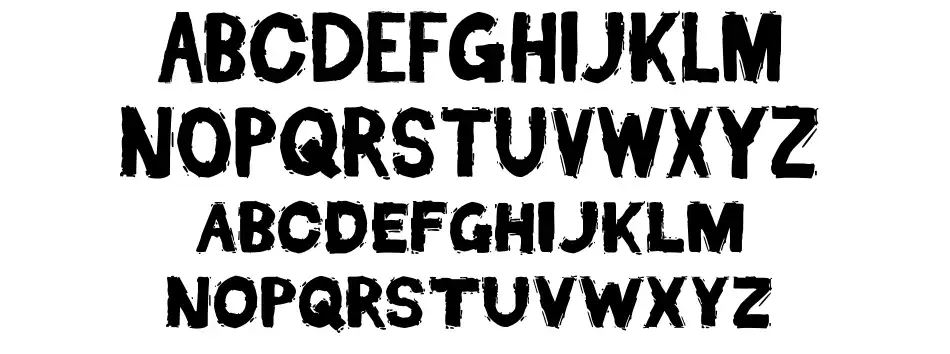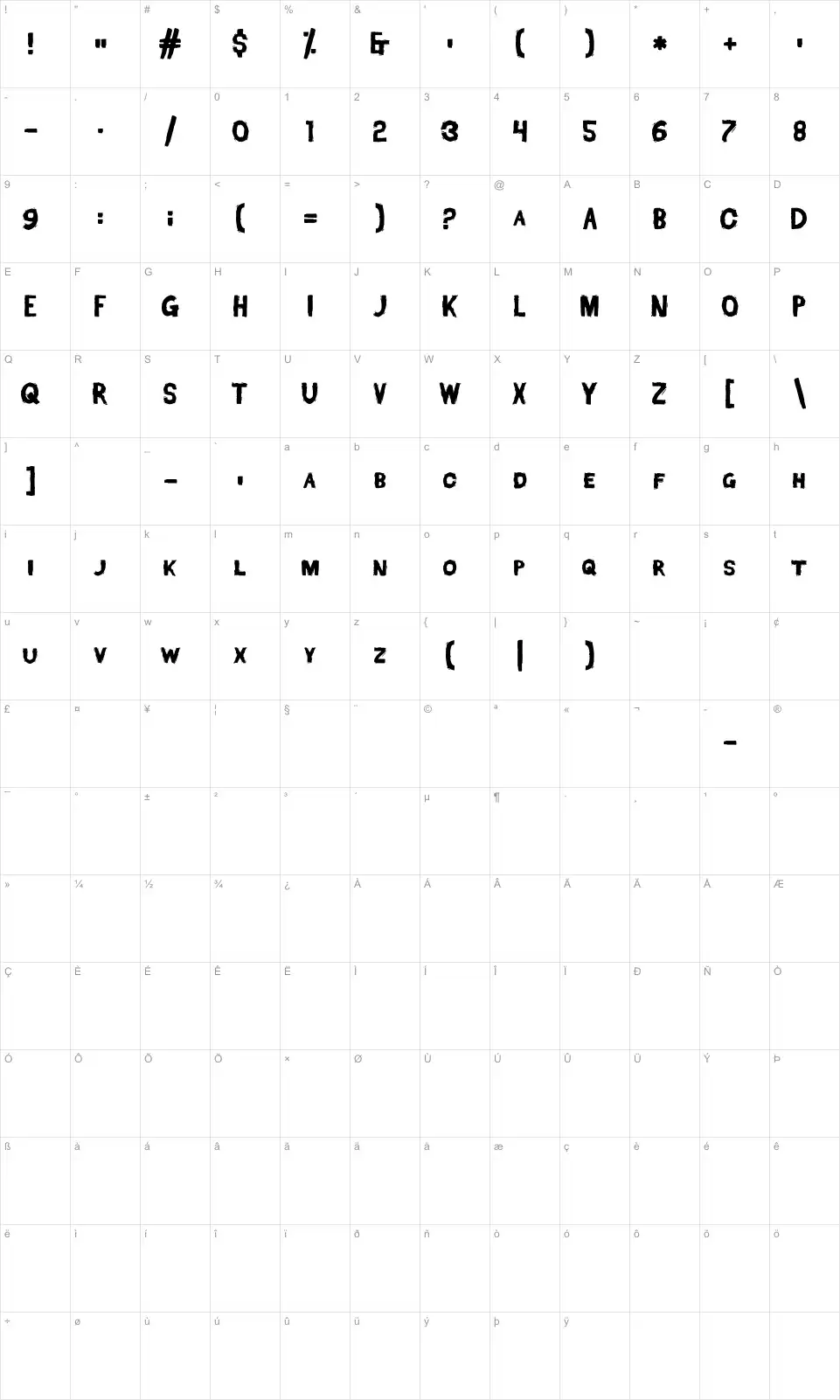
A fonte ‘Dead Font Walking’ é um design assustador criado por Andrew McCluskey, disponível para download. Para quem busca algo um pouco diferente no mundo das fontes, a ‘Dead Font Walking’ é uma excelente escolha. Com categoria “Fancy > Horror”, esta fonte adota elementos macabros e sombrios, certamente agradando os amantes de estilos menos convencionais. Licenciada sob a licença gratuita, a ‘Dead Font Walking’ pode ser usada sem preocupações legais. Com 16 KB de tamanho, esta fonte OTF é compacta e adequada para uso em projetos digitais de pequeno a médio porte. Adicionada no dia 12 de julho de 2022, a ‘Dead Font Walking’ já teve seu download confirmado 4752 vezes, o que é uma ótima indicação de sua popularidade. Visite o site do designer, http://nal.so, para obter mais informações sobre este fascinante design.
Categoria: Fancy › Horror
Designer: Andrew McCluskey